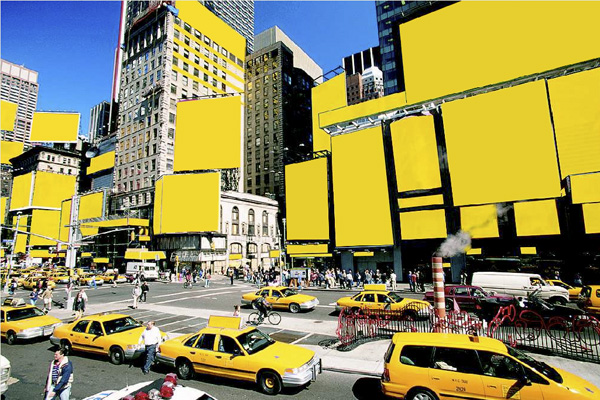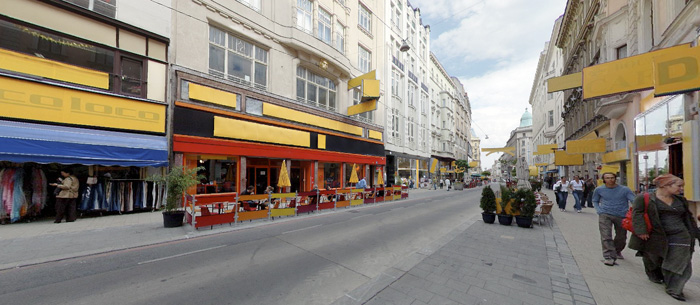
Bitte: Keine Welt ohne Schrift!Es wird viel geschimpft über Werbung in den Fußballstadien,
Plakatwände im öffentlichen Raum und Megaposter an Hausfassaden. Die
österreichischen Künstler Christoph Steinbrener und Rainer
Dempf haben im Juni in der Wiener Neubaugasse alle Beschriftungen
gelöscht. »Delete! Die Entschriftung des öffentlichen Raums«
heißt das Projekt, zu dem es jetzt eine aufschlussreiche Webseite gibt.
![]() ![]() »Wenn die Schilder wieder enthüllt werden, wird die Wahrnehmung eine andere sein,« prophezeite Christoph Steinbrener, der vom 6. – 20. Juni auf der Wiener Neubaugasse bis zur Ecke Lindengasse alle kommerziellen Schriftsignale verschwinden ließ. Er nennt den Vorgang »Entschriftung«, ein Projekt, das er gemeinsam mit Rainer Dempf entwickelt hat. ![]() Die beiden Künstler reagieren mit der Entschriftung auf die überquellende Masse an Konsumbotschaften im öffentlichen Raum. Mit monochromen rapsgelben Überklebungen decken sie sämtliche Beschriftungen ab ... keine Bereinigung, sondern eine Markierung: »Die Leute in der Stadt schauen nicht mehr richtig hin, sondern sie nehmen hin«, beschreibt der Typograph Dempf die Abstumpfung der Stadtbewohner angesichts zunehmender und aggressiverer Werbeformen. Wie sieht der New Yorker Times Square entschriftet (und entbildert) aus:
Auf der Webseite zur Aktion kann man die Entschriftung des Times Square im Zeitraffer bewundern Spaziergang über die Neubaugasse im Quicktime-VR-Rundumblick:
Auf dieser Seite laden Sie sich den QuickTime-VR-Rundgang ... Das Ziel von Steinbrener und Dempf ist, »delete!« in modifizierter Form auf andere Städte, beispielsweise Hamburg oder Tokio zu übertragen. Aber auch in Zeitungen könnte mit dem Prinzip gespielt werden. Die beiden planen ein »typografisches Verwirrspiel« mit kleinen subtilen Eingriffen, ohne dass die Lesbarkeit Schaden nimmt. Mitunter stehen zwischen den verwendeten Schrifttypen – beispielsweise Garamond und Fleischmann – 200 Jahre Schriftentwicklung, erklärt Dempf, der einst »statt Lateinvokabeln das FontBook auswendig gelernt hat«. Reaktionen auf die Wiener Aktionswoche gabe es auch: Ein Geschäft in der Neubaugasse will die eigenen Werbeformen überdenken und entfernt alle Beschriftungen, um etwas ganz Neues zu machen. Herausgegeben: Fr - Dezember 9, 2005 at 03:10 nachm. | |